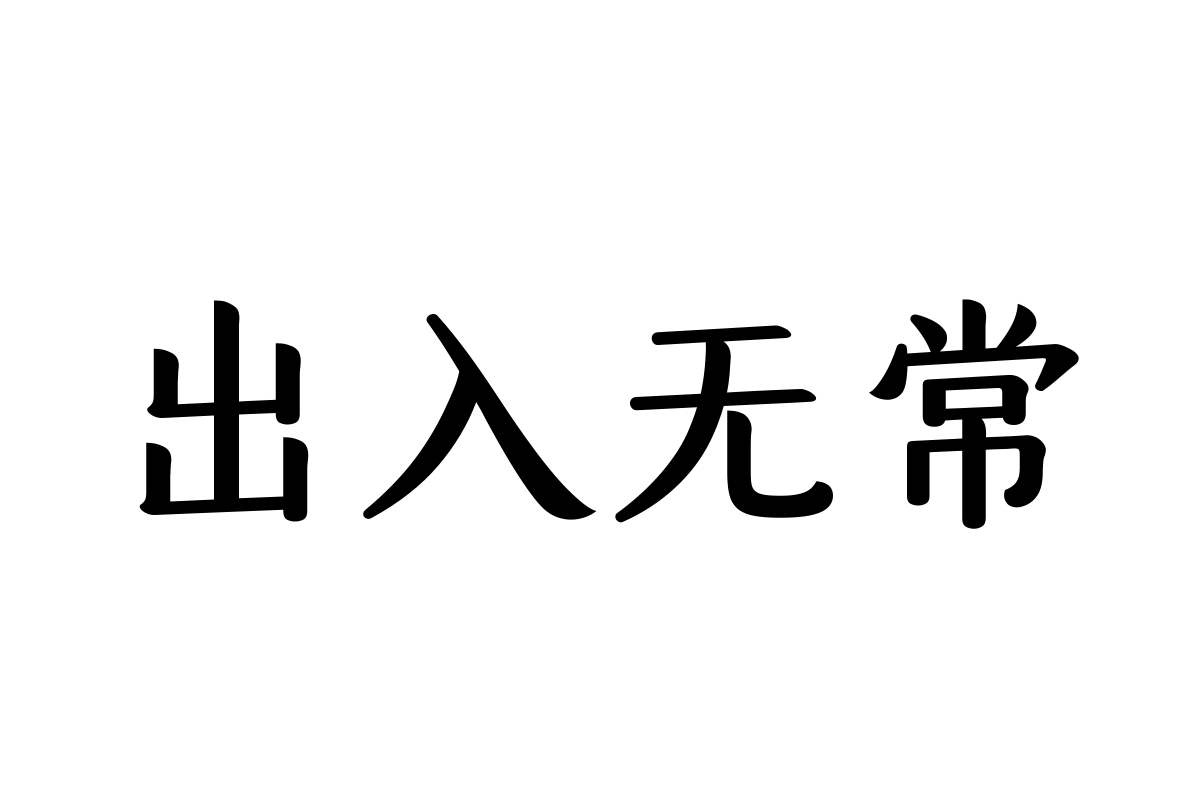
汉仪空山楷是一款具有现代感和简洁风格的字体,适用于需要强调文字的场合。这款字体的特点是笔画流畅,结构紧凑,给人一种清晰、易读的感觉。它的线条粗细适中,既不会过于粗犷,也不会过于纤细,适合用于各种类型的文本设计。此外,汉仪空山楷还具有一定的装饰性,可以增加文字的美感和艺术感。总的来说,汉仪空山楷是一款非常适合现代设计需求的字体。